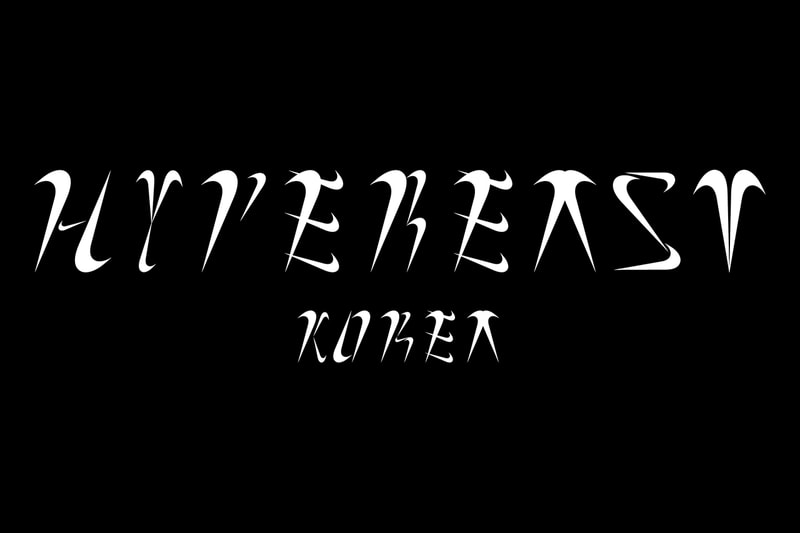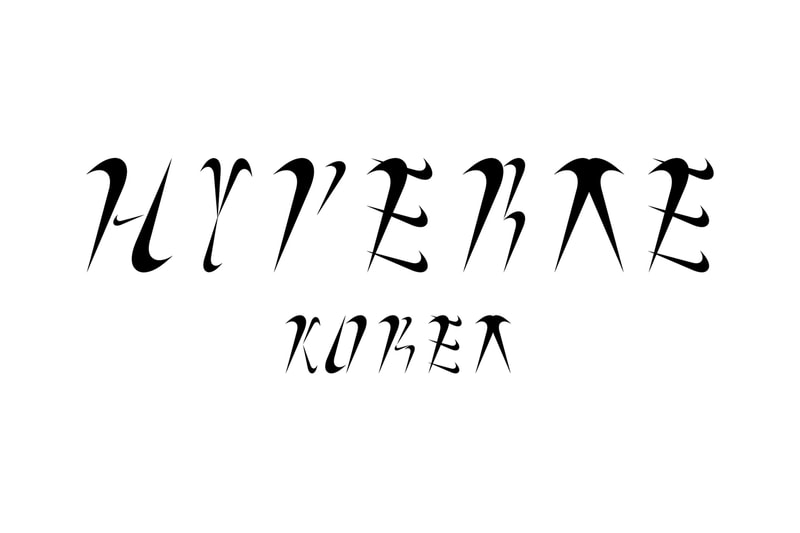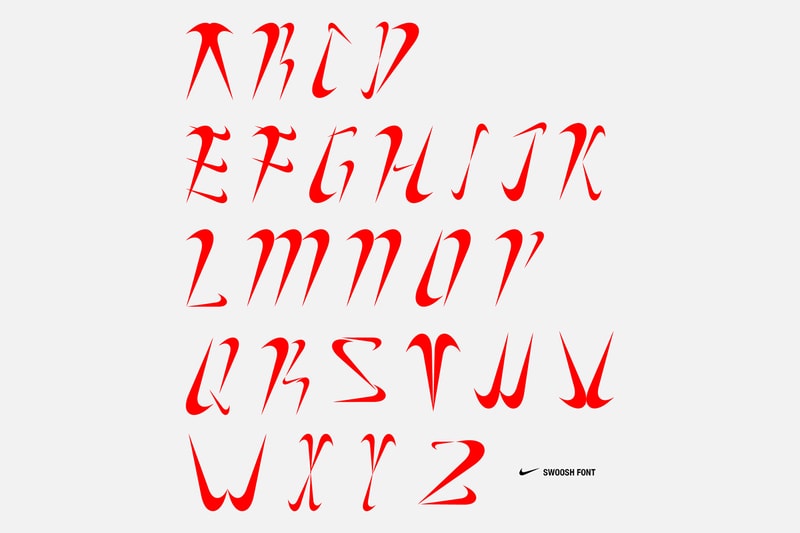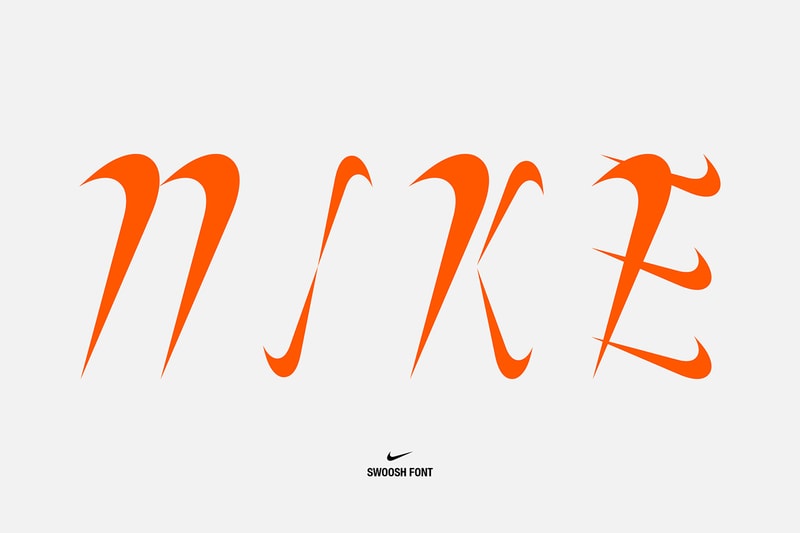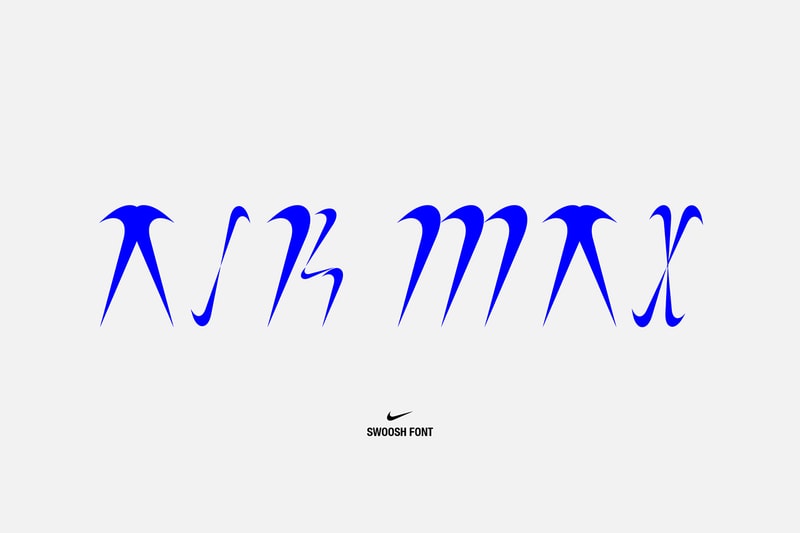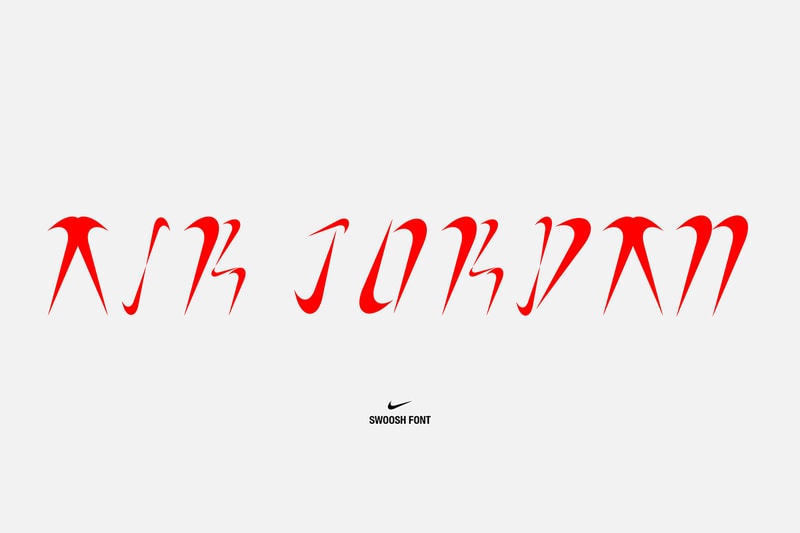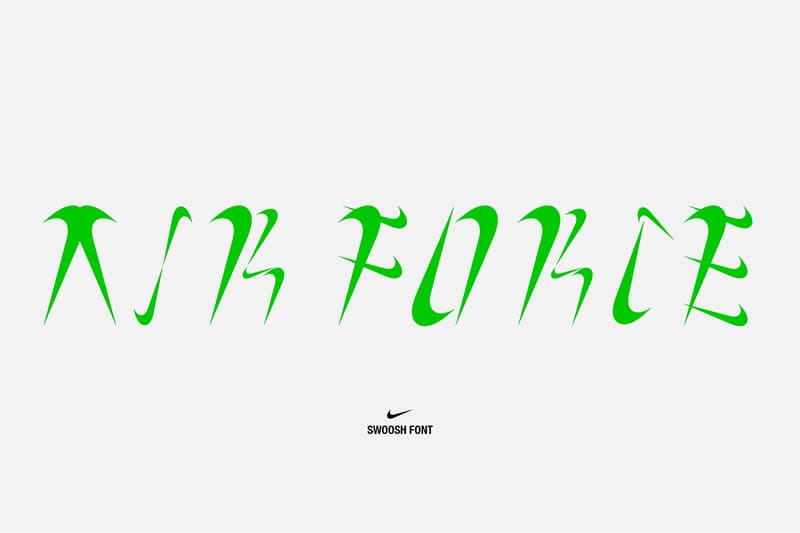
에어 맥스 97 ‘네온 서울’ 디자이너가 ‘나이키 스우시’로 만든 폰트는?
신광의 ‘나이키체’를 확인해보자.
나이키의 스우시 로고를 활용한 폰트가 공개됐다. 해당 폰트를 제작한 디자이너 ‘신광’은 2018년 개최된 ‘나이키 온에어 디자인 컴피티션’에서 한국의 국기인 태극기와 서울의 밤에 많이 볼 수 있는 네온사인에 영감을 받은 에어맥스 97 ‘네온 서울’을 출품해 최종 우승을 차지한 인물이다.
신광은 인스타그램을 통해 “스우시로만 서체를 만들어보면 어떨까?”라는 아이디어에서 시작해 현재까지 만들어진 서체가 없는 것을 확인하고 작업을 진행하게 됐다고 밝혔다. 그는 ‘A’를 만들기 어렵지 않았고, 스우시를 90도로 세우면서 오블리크 스타일로 디자인 구현이 가능할 것 같다고 판단해 ‘Z’까지 디자인 작업을 그대로 마무리했다고 이야기했다. 스우시 끝의 삐침이 세리프체처럼 보이는 것이 특징.
상단 갤러리에서 ‘A’부터 ‘Z’까지의 ‘스우시 폰트’와 해당 폰트로 쓴 ‘AIR JORDAN’, ‘AIR MAX’, ‘AIR MAX’ 등 나이키의 대표 스니커 모델의 이름들 그리고 작가가 직접 제작한 <하입비스트> 코리아와 <하입배> 코리아의 디자인 이미지를 확인할 수 있다.